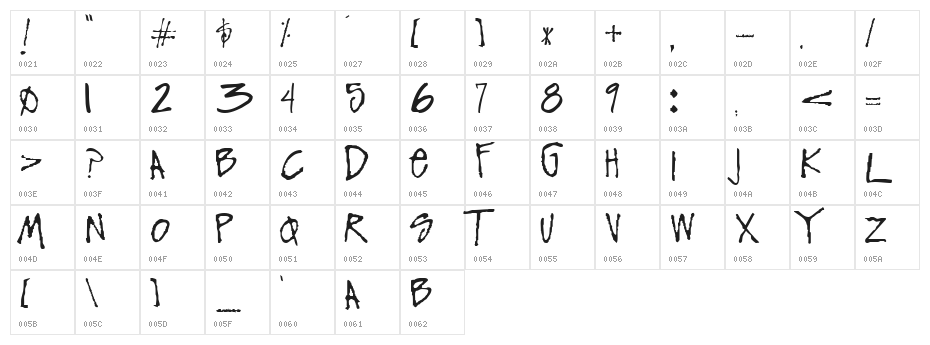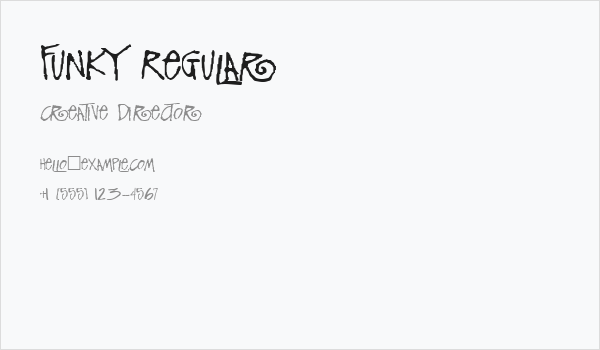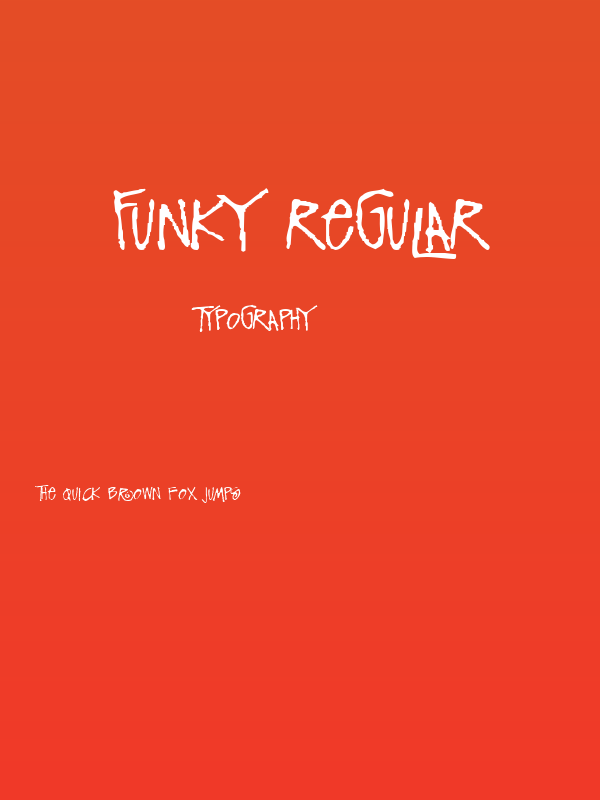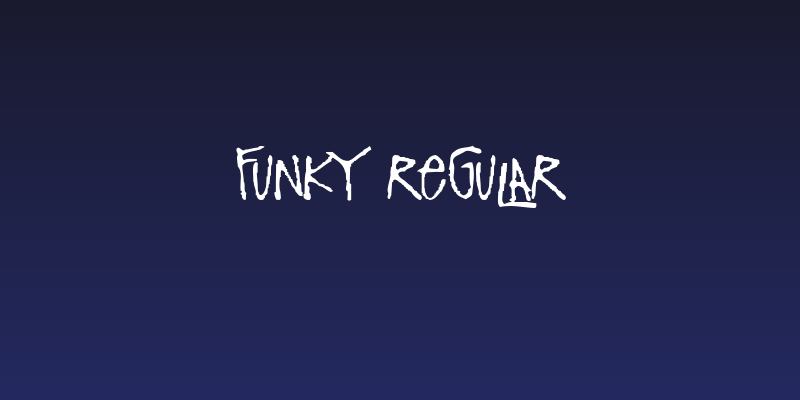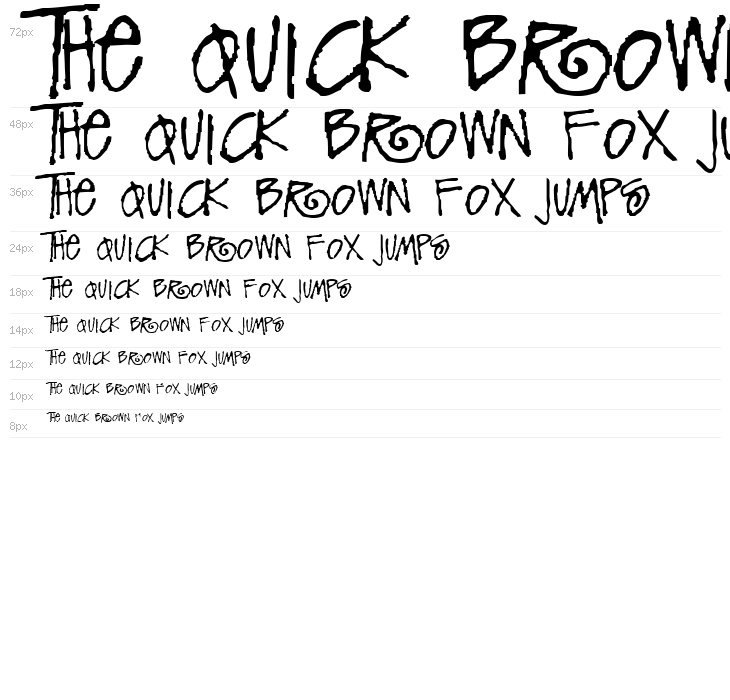
Funky Regular Font
✎ Quirky
| Progetti proposti | Ideal for children's books, comic strips, playful branding, or any project seeking a fun and informal touch. |